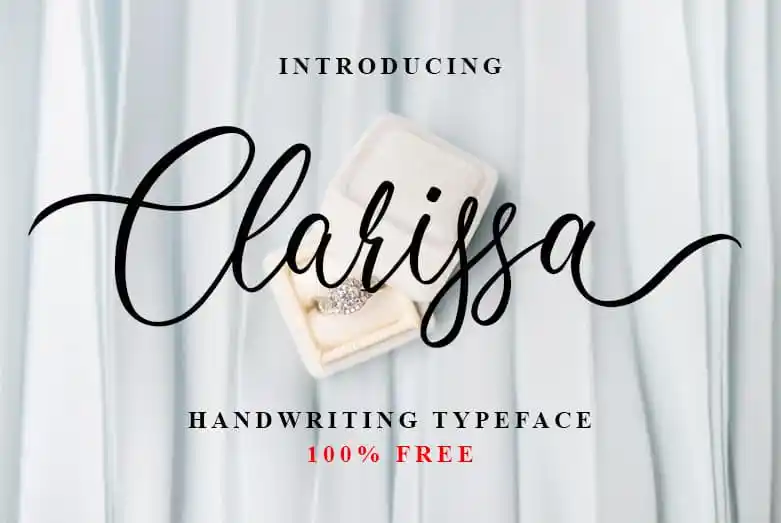
Clarissa Calligraphy Font – Download Grátis
A Clarissa Calligraphy Font é uma escolha perfeita para quem busca uma escrita elegante e moderna. Inspirada na calligrafia clássica, essa fonte apresenta linhas suaves e finas, complementadas por ligamentos femininos e sofisticados que não comprometem a leitura fácil e fluida. Ela é perfeita para criações gráficas requintadas e sofisticadas, como logotipos de marca, texturas editoriais ou qualquer elemento visual que deseje destacar com um toque elegante. Se você procura uma fonte de calligrafia que combine modernidade e classe, a Clarissa é uma ótima escolha. Além disso, oferecemos alternativas estilísticas para múltiplos caracteres, garantindo diversidade e personalização. Este é mais um recurso gráfico adicional para enriquecer seus projetos digitais com uma escrita única e sofisticada.